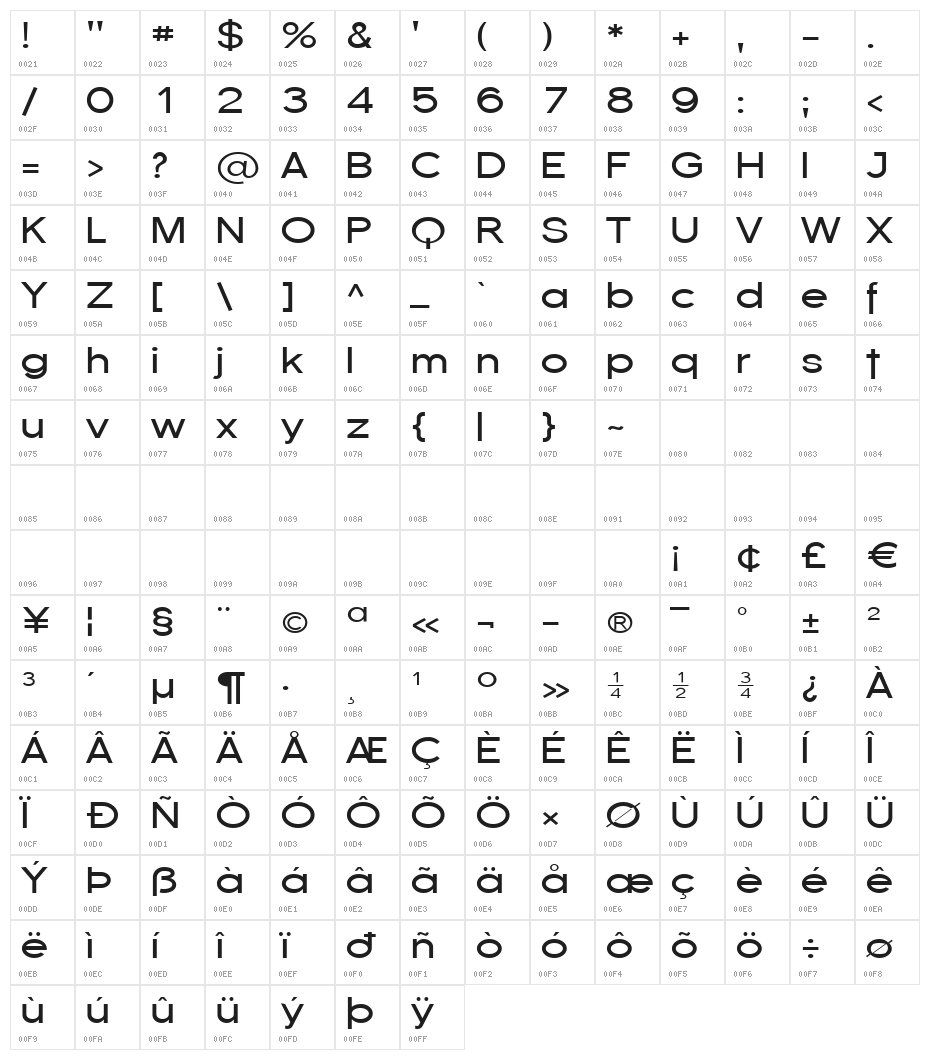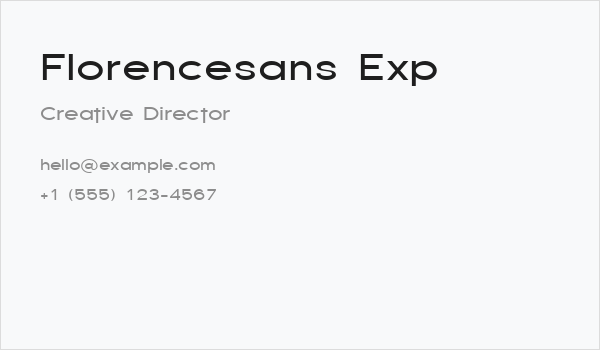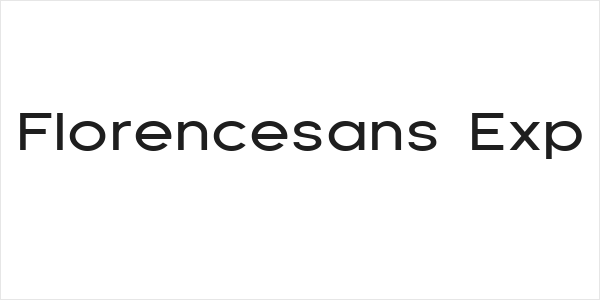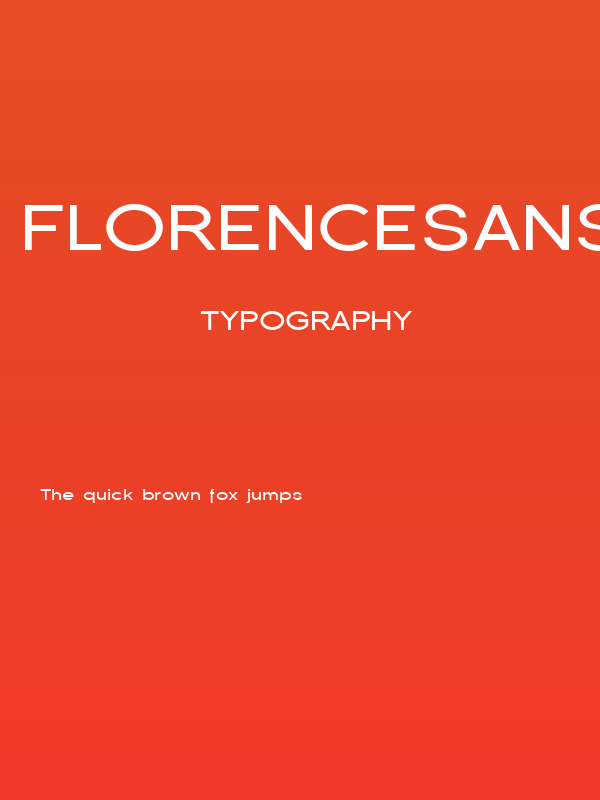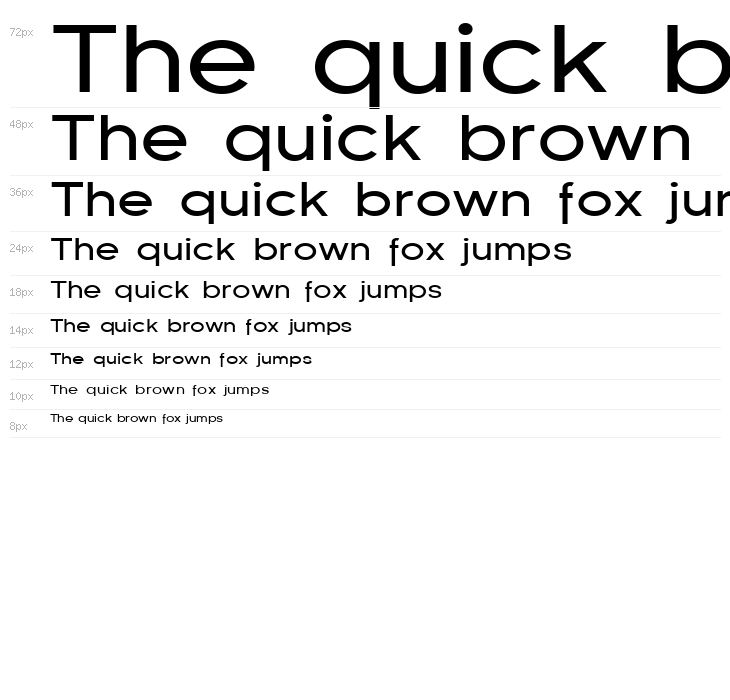
Florencesans Exp Font
| Caso de uso | Headlines, Body text, Logos |
| Proyectos propuestos | Ideal for branding, advertising, web design, and editorial projects where a modern and clean aesthetic is desired. |